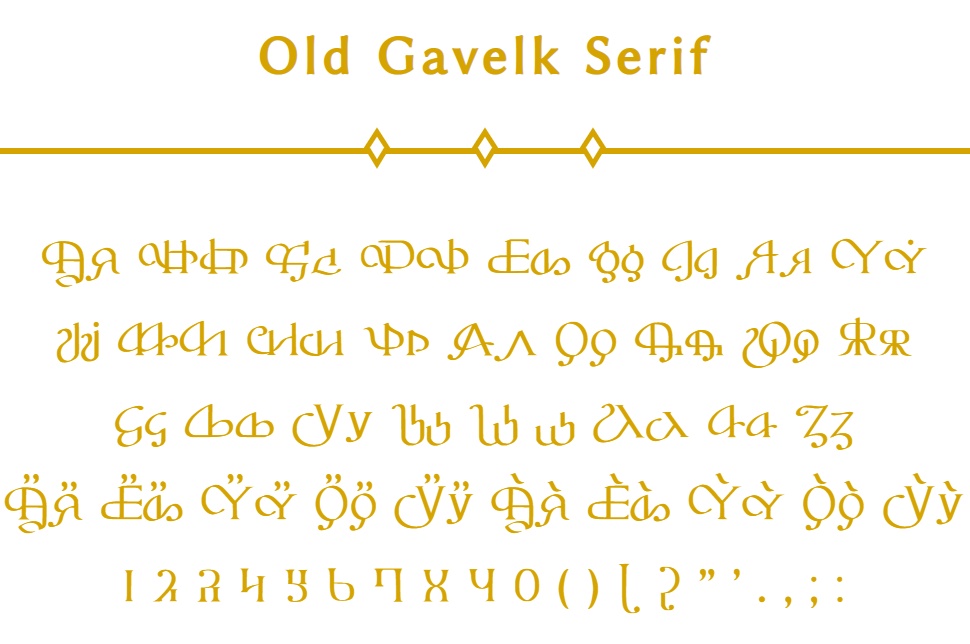
Fantasy Font | Old Gavelk Serif
ファンタジー系のTRPG等で使うことを想定して制作したフォントです。 「Gavelk Sans」よりも更に古い、魔法で動く機械が使われていた時代の文字を意識して制作しました。 ---- 「Fantasy Font シリーズ 全6書体全部入りセット」をご購入すると格安で入手できてお得です。ぜひこちらをどうぞ! https://soya-workshop.booth.pm/items/4766747
使用文字見本
Aa Bb Cc Dd Ee Ff Gg Hh Ii Jj Kk Ll Mm Nn Oo Pp Qq Rr Ss Tt Uu Vv W w Xx Yy Zz Ää Ëë Ïï Öö Üü Áá Éé Íí Óó Úú 1 2 3 4 5 6 7 8 9 0 ( ) ! ? " ' . , ; :